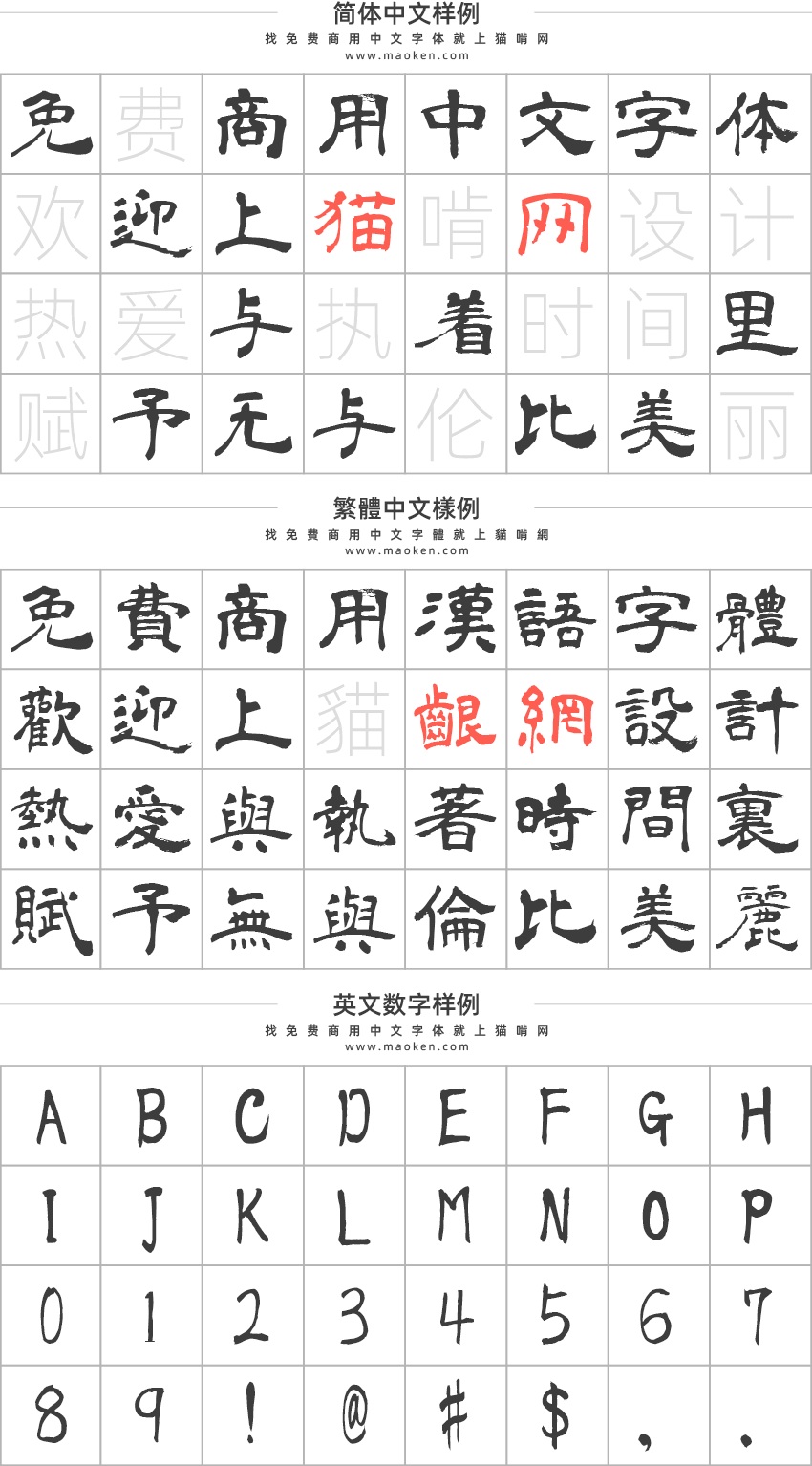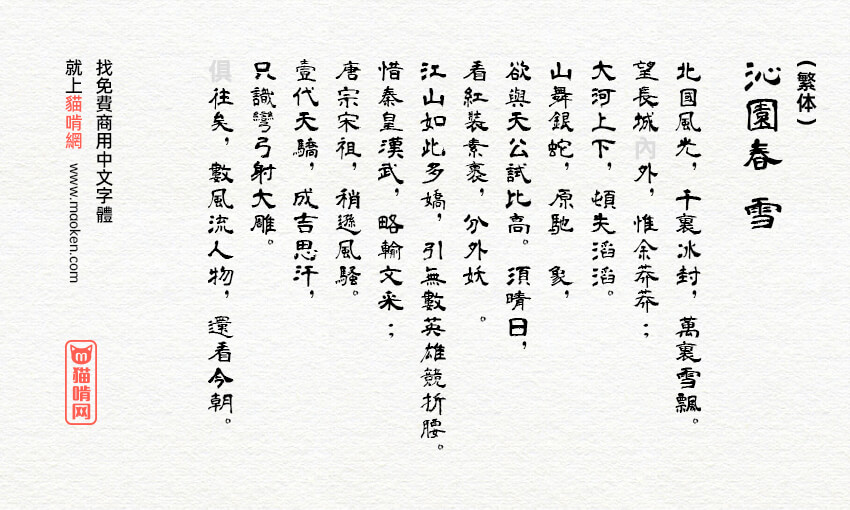
青柳隶书:日本青柳衡山挥毫隶书字体免费商用
字体作者:青柳衡山 (其他语种) 字体字重:1个
字体名称:青柳隶书(日文名: 青柳隷書しも )PS中字体名称:青柳隷書SIMO2_T Regular
青柳隶书是日本书法家青柳衡山老师题字的,然后是SIMO先生制作成TrueType字体。这款字体包含JIS第1水准2965字,第2水准3390字。由于字体采用的日本的JIS标准,所以支持的简体字数不算多,但是繁体却是比较齐全的。隶书的免费字体很少见,所以对古典风格的设计等很有用。